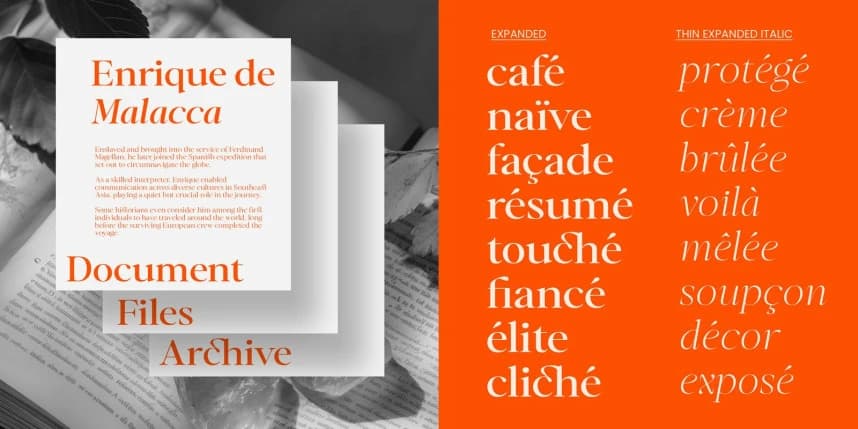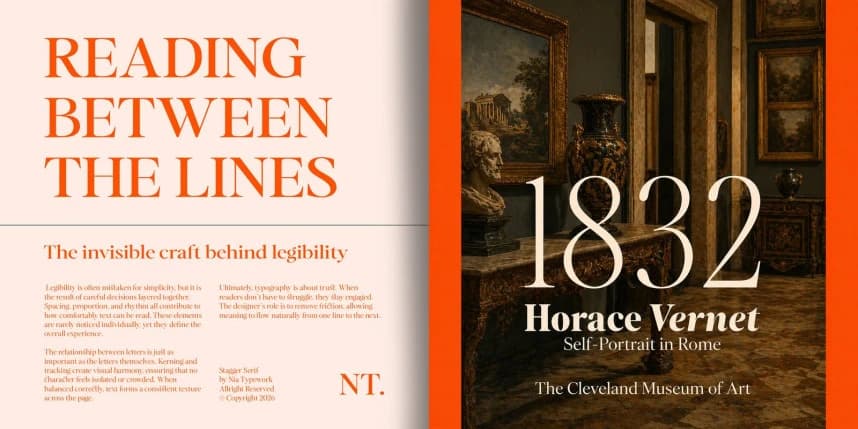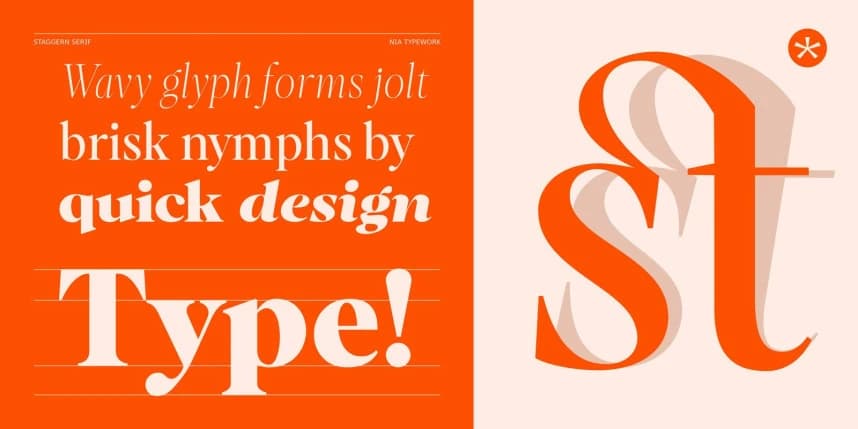
Stagger Yazı Tipi Ailesi
Stagger Font Family modern bir serif yazı tipidir ve cesur, ifade dolu bir karaktere sahiptir. Değişken bir font ailesi olarak tasarlanmıştır; roman stilinden gerçek italiklere kadar geniş bir stil yelpazesiyle kapsamlı esneklik sunar. Güçlü harf biçimleri, ince kontrast
Stagger Font Family modern bir serif yazı tipidir, cesur ve ifadeli bir kişiliğe sahiptir. Değişken bir font ailesi olarak tasarlanmıştır ve romandan gerçek italiklere kadar geniş bir stil yelpazesine sahip esneklik sunar. Güçlü harf biçimleri, ince kontrast